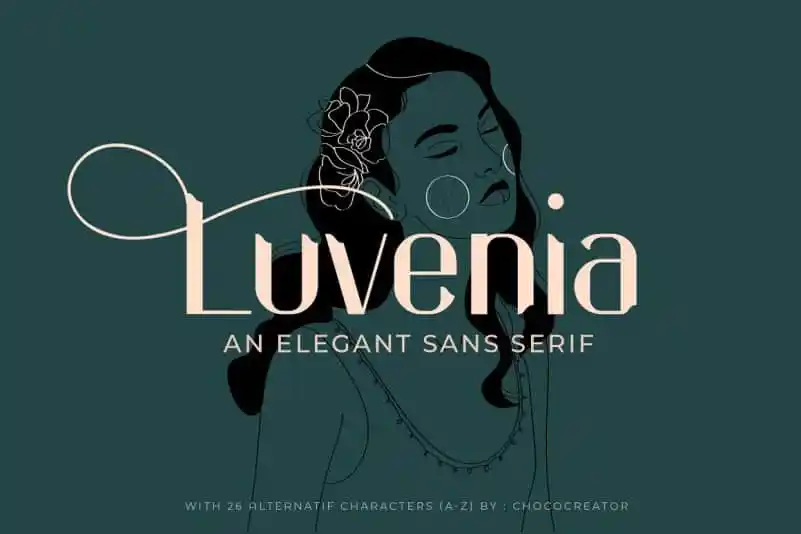
A Luvenia Sans Serif Font é uma escolha perfeita para quem busca estilos simples e elegantes para seus projetos visuais. Criada com simplicidade, minimalismo e luxo como principais diretrizes, essa fonte moderna traz um toque de sofisticação. Desenvolvida pelo Missingfont.std, ela oferece uma ampla gama de caracteres especiais belamente formados, alternativas personalizadas e ornamentações, adaptada para suporte a várias línguas. Com seu design elegante e minimalista, Luvenia Sans Serif é ideal para trabalhos de identidade visual como criação de logomarcas, embalagens de roupas, cabeçalhos de revistas ou até mesmo textos estilosos sobre fundos de imagem que precisam de um ar refinado. Este fonte flexível se adapta perfeitamente tanto em grandes tamanhos quanto em versões menores, tornando-o uma opção conveniente para diversos ambientes gráficos.